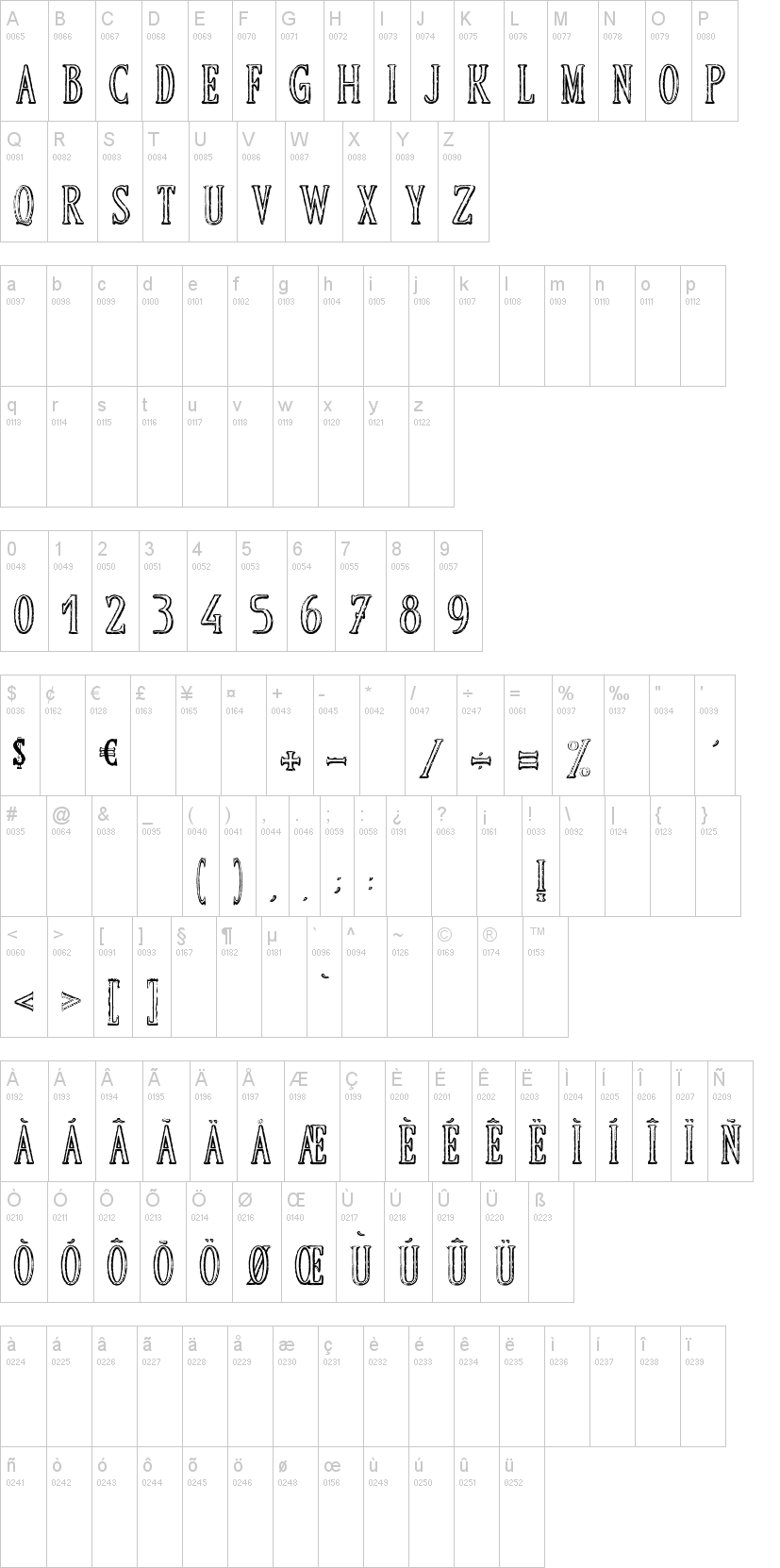
Hercule VS Golliath
Hercule VS Golliath是一款免费的英文字体,由设计师Pierre Terrier创建。这款字体的灵感来自于古希腊神话中的希拉克勒斯(Hercules)和巨人歌利亚特(Goliath)之间的传说。字体的特点是粗壮而具有冲击力的外观,具有独特的手写风格和现代感。该字体适用于标题、海报、标志、广告等大型设计项目,因为它可以很好地吸引人们的注意力并传达出强烈而有力的信息。
Hercule VS Golliath是一款非常不错的手写艺术字体,具有很好的视觉感,适合于文化类的宣传设计、商业类品牌的广告和产品包装设计以及个性化文字排版等较多场景。
Hercule VS Golliath字符映射图